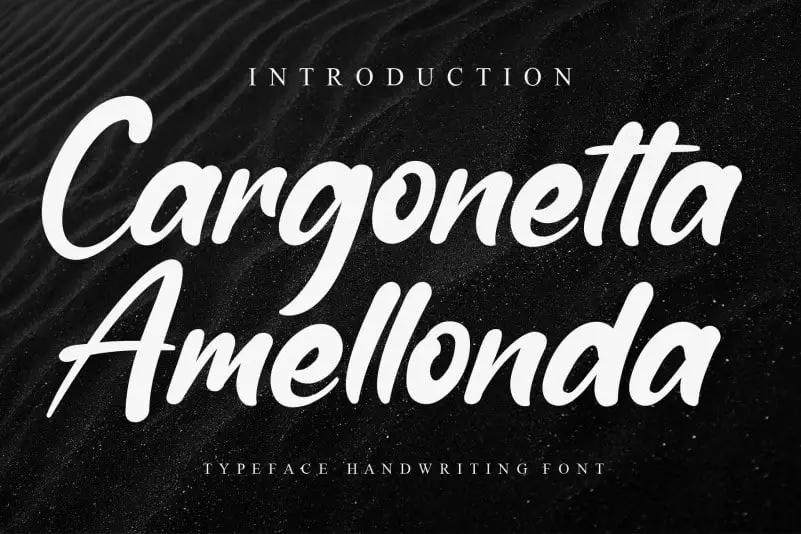
Cargonetta Amellonda Script Font – Download Grátis
A Cargonetta Amellonda Script Font é uma fonte escrita a mão criada para oferecer experiências únicas aos designers digitais. Seu design delicado e elegante proporciona um toque especial ao seu trabalho, tornando-o único e imediatamente reconhecível. Ideal para aplicar em textos de marketing, anúncios publicitários ou até mesmo em gráficos de moda e arte contemporânea, a Cargonetta Amellonda Script oferece uma linguagem de texto que flui naturalmente nas criações. Seu design é fluido e expressivo, permitindo aos criativos expressar sentimentos e ideias de forma incrivelmente personalizada. O designer especializado andikastudio criou esta fonte para atender às necessidades dos designers que desejam dar um toque único à sua obra, tornando a Cargonetta Amellonda Script uma escolha excepcional entre as opções de fontes escrita a mão disponíveis. Não espere mais e aproveite essa oportunidade única para enriquecer suas criações com uma fonte de alta qualidade.